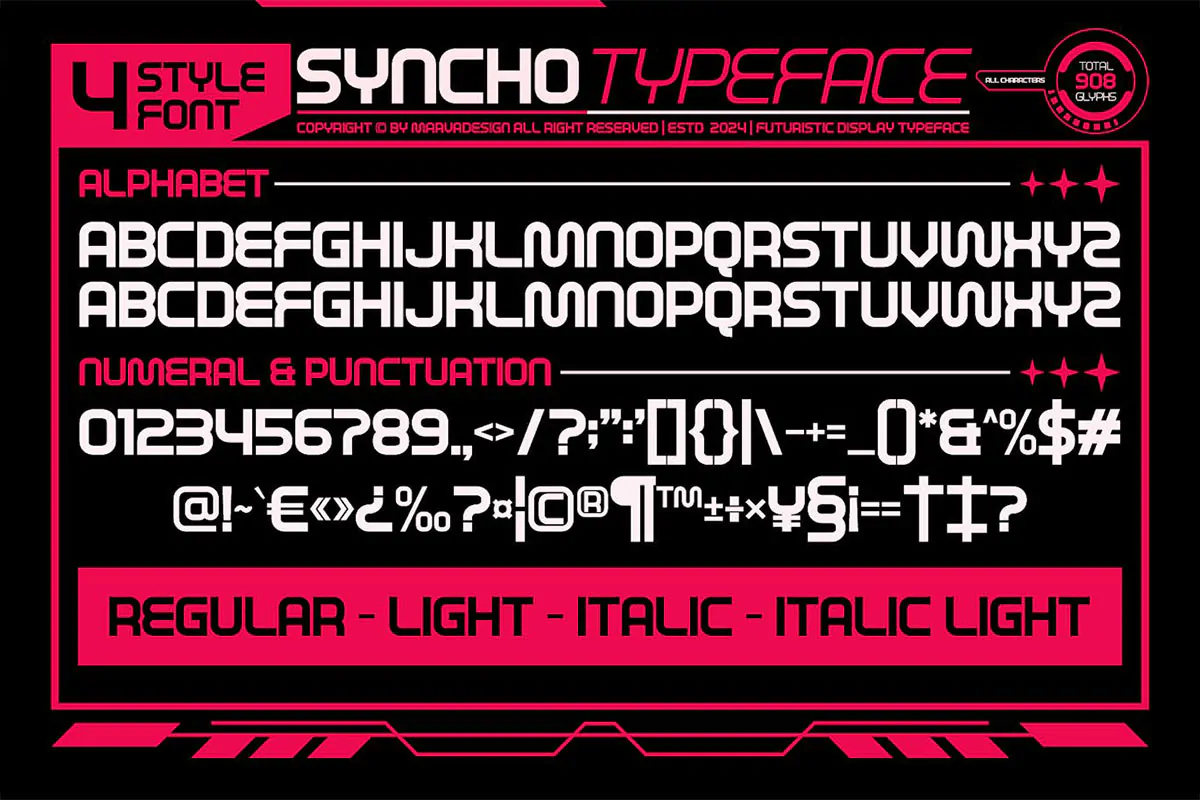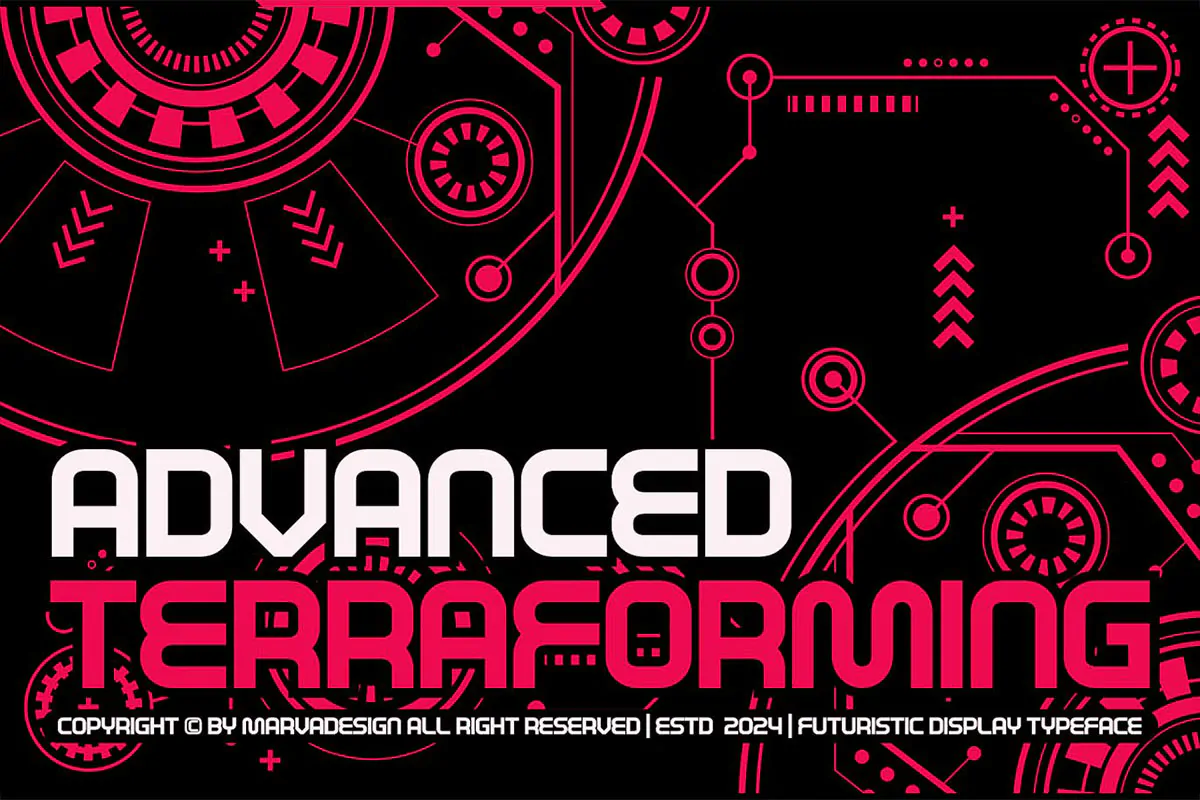
سریف فونت مدرن Syncho
سریف فونت مدرن
سریف فونت مدرن Syncho یک قلم انگلیسی زیبا است که مناسب برای استفاده در تیتر و عناوین طرحهای گرافیکی مختلف از جمله طراحی انواع تراکت، بروشور، پوستر و … میباشد.